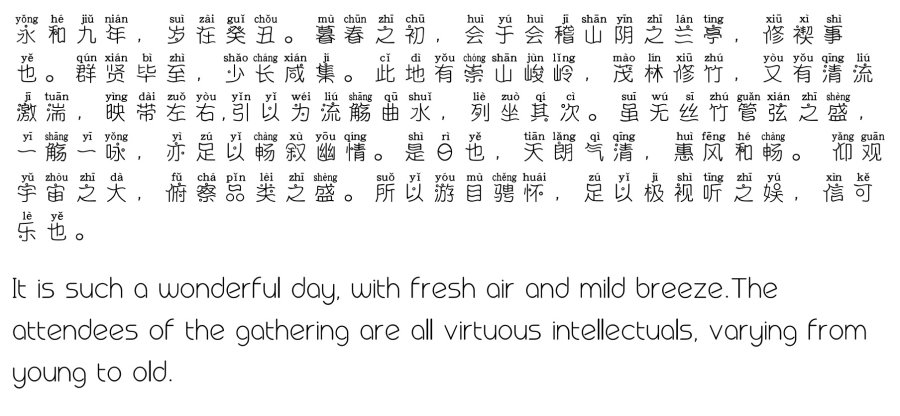
艺术字体在最近这些年挺火爆的,因为现在大多数年轻人都开始追随个性,拒绝死板,从现在的穿衣打扮就可以看得出来。二次元拼音体字体也不例外。
除了这些之外,随着互联网的发展,对于字体的要求也越来越多了,什么时候用什么样的字体,在这方面还是比较讲究的,相信不少人也都了解过。今天义启字库带各位了解一下二次元拼音体,带大家走进二次元的世界
了解二次元拼音体
二次元拼音体字体,是一个独具特色的艺术字体,采用了二次元的设计风格,可以用于动漫设计艺术设计,运用的领域比较广泛,尤其是一些喜欢艺术的朋友,在各种设计中可以运用到这种字体,确实是一个不错的选择。
不少人在制作海报或者制作文档时,就可以运用到这种字体,可以轻松的让你展现出你的风采,展现出个人的特点。个人还是挺喜欢这种二次元的,尤其是那些二次元少女,特别符合那种独特的感觉。
带你走进二次元世界
这种字体是一个充满二次元气息的字体,看起来也比较可爱,字体整体,非常流畅,有一种波浪感,下划线也变得非常性感。更主要的是还加上了拼音,让整个字体显得更个性了,符合一些年轻人的个性。